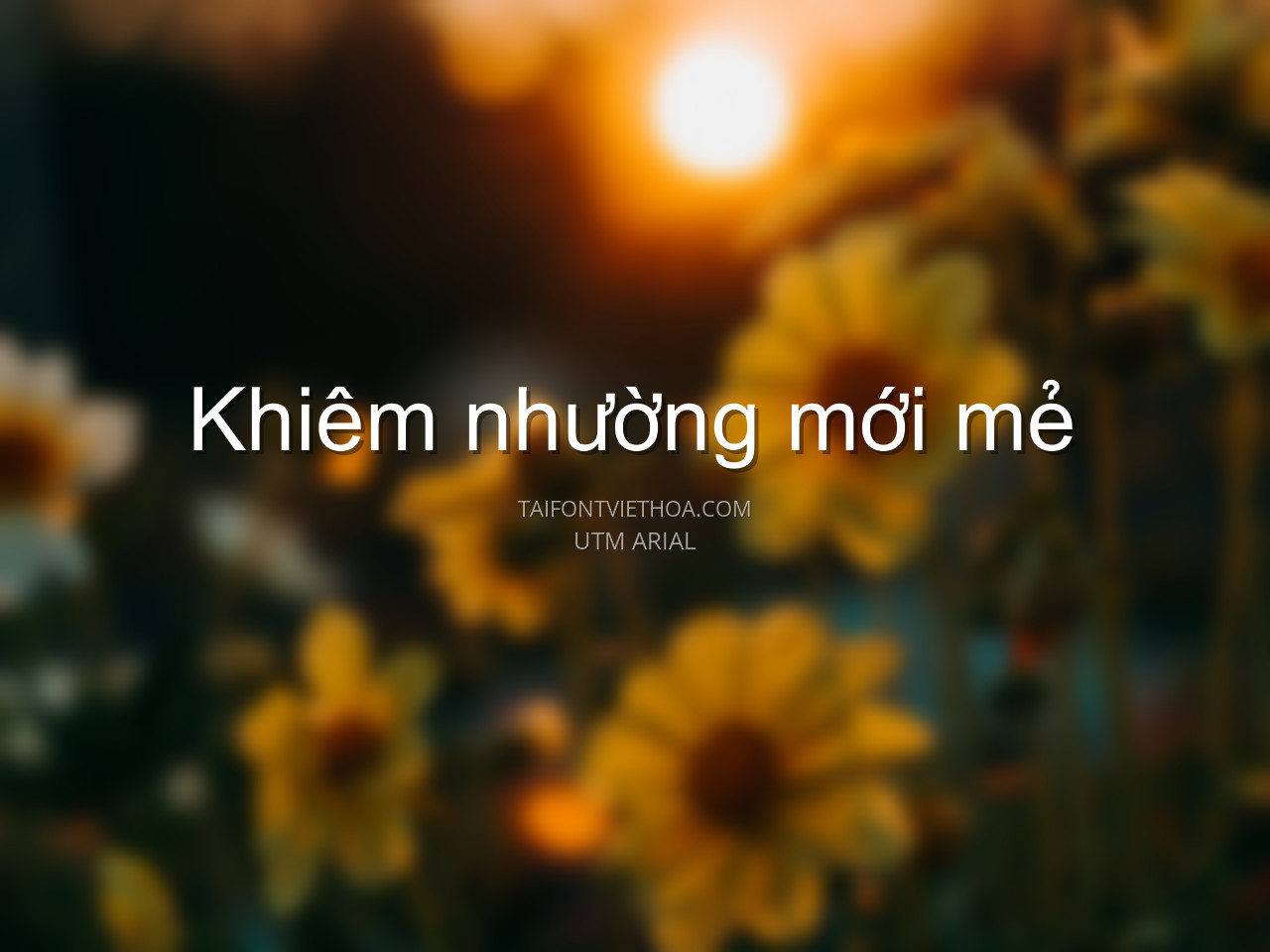
Giới thiệu về font UTM Arial
UTM Arial là phiên bản Việt hóa của font Arial – một trong những kiểu chữ sans-serif phổ biến và được sử dụng rộng rãi nhất trên thế giới. Font Arial được phát triển bởi Monotype vào năm 1982, nổi bật với thiết kế đơn giản, rõ ràng và dễ đọc trên nhiều nền tảng kỹ thuật số và in ấn. Phiên bản Việt hóa UTM Arial đã được tối ưu để hỗ trợ đầy đủ tiếng Việt cùng hơn 200 ngôn ngữ khác, giúp mở rộng khả năng sử dụng trong các dự án thiết kế đa dạng.
Đặc điểm thiết kế và ứng dụng của UTM Arial
UTM Arial sở hữu cấu trúc sans-serif không chân, các nét chữ gọn gàng, đồng đều và cân đối, tạo cảm giác hiện đại và dễ đọc. Font có độ dày vừa phải, phù hợp với cả tiêu đề và văn bản nội dung dài. Thiết kế font tập trung vào sự đơn giản và hiệu quả truyền tải thông tin, giúp tối ưu trải nghiệm người dùng trên mọi thiết bị.
Font phù hợp sử dụng trong các dự án thiết kế website, tài liệu văn phòng, ấn phẩm quảng cáo, nhận diện thương hiệu, và nhiều ứng dụng khác. Các ngành nghề sử dụng phổ biến gồm: công nghệ, giáo dục, truyền thông, kinh doanh và thương mại điện tử.